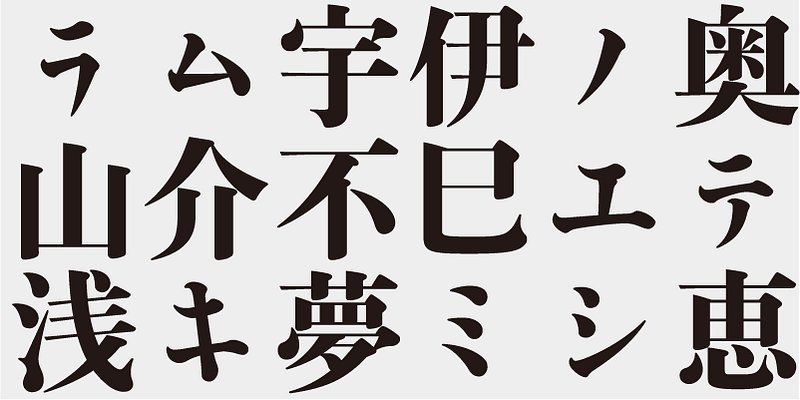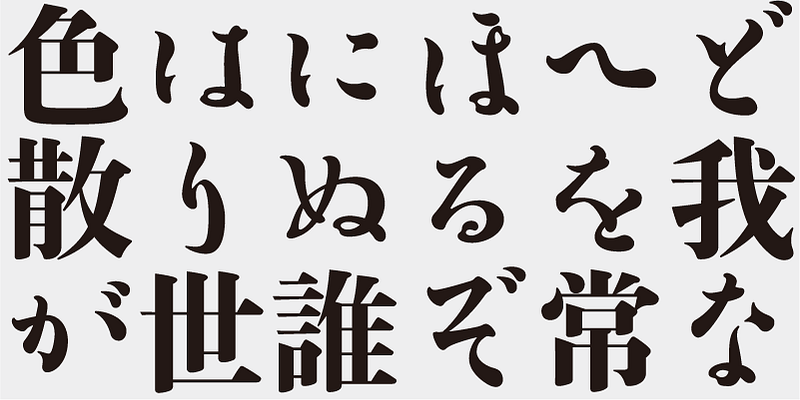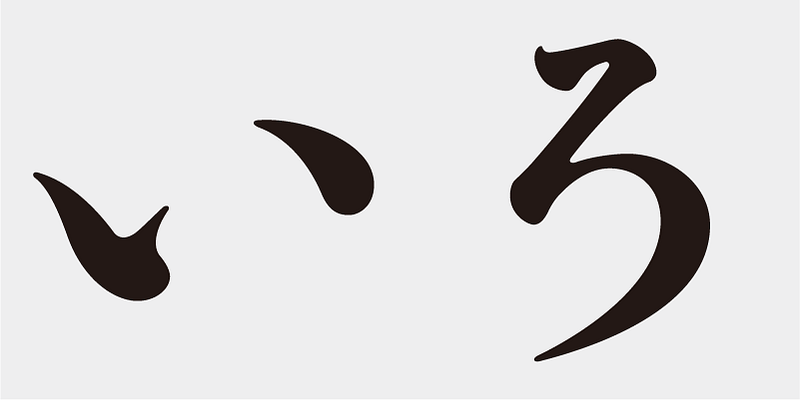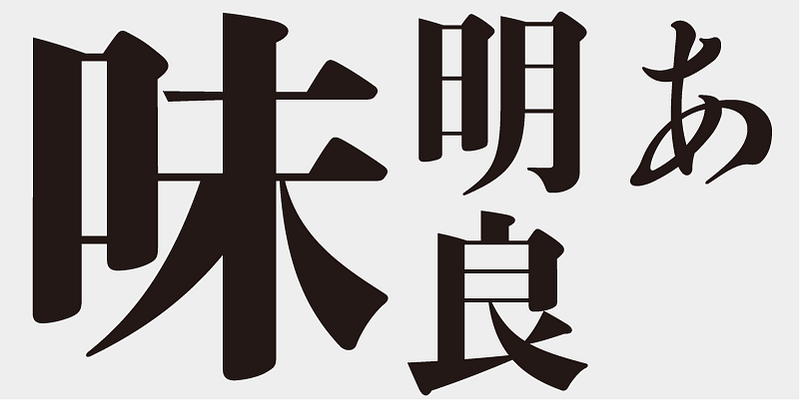
「味明」は活字の匂いはするが、単なる復刻とは違う、新しい見出し明朝体を目指しました。それはどのような明朝体かといえば、欧文フォントの「Bodoni」のように、縦画がくっきりと太く垂直、横画は細く水平で、エレメントはしっかりと強い明朝体です。
小サイズで使ってもつぶれませんが、ポスターなど、大きなサイズでの使用を想定してデザインしています。大きなサイズに使えば使うほど、エレメントの美しさが発揮されます。
江戸時代後期の禅僧「良寛」(1603–1868) は、唐の「懐素」などから学び、あたたかく、人間味あふれる自由奔放な独自の墨跡を数多く残しました。
味岡伸太郎かなシリーズ「良寛」は、その墨跡から骨格を求めたもので、独創的でありながら、仮名本来の伝統的な形を持っています。しかし、現在使われているひらがな、カタカナの字体のすべてが良寛の遺墨で見つかるわけではなく、字体が異なる、いわゆる変体仮名とされる字体も使われています。それらは、良寛の他の字体を参考にして創作したものです。今回発表の「味明 良/EB」は、かなシリーズ「良寛」を「味明」スタイルに合わせて、30年ぶりにリデザインしたものです。
このフォントには、新聞社、出版社、国語研究所等の使用頻度表から選んだ上位 1,000 文字の漢字に加え、206 文字の両仮名および約物が含まれています。
「味明」は活字の匂いはするが、欧文フォントの「ボドニ」のように、縦画がくっきりと太く垂直、横画は細く水平で、エレメントはしっかりと強い、これまでにない見出し明朝体です。エレメントをさらにシャープにした「味明Modern」は豊かさとシャープを兼ね備えたエレガントな明朝体です。そして最大の特徴は、筆記体に近いものから、活字の復刻やモダンな仮名まで、10種の仮名をセットしたことです。これだけのバリエーションがあれば、「味明」シリーズ一つで、あらゆる用途に使えるでしょう。